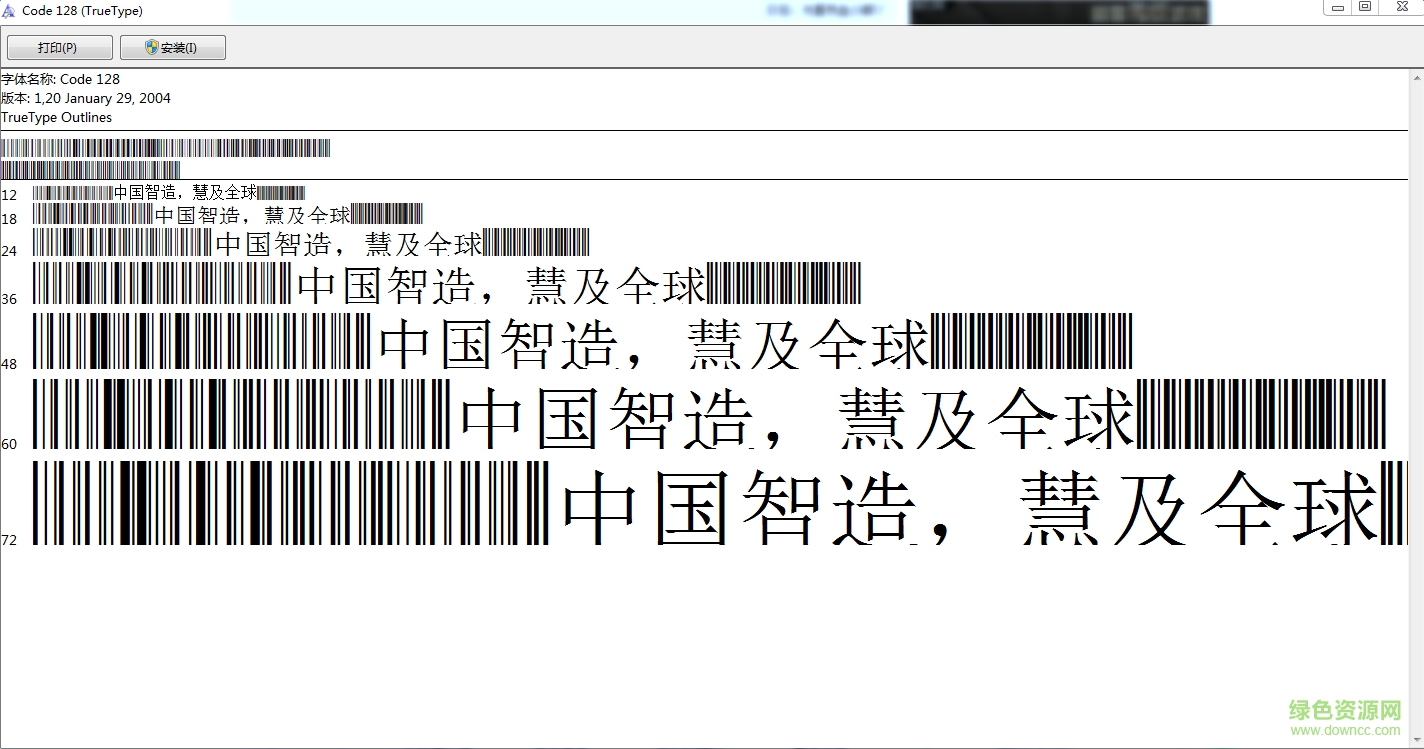
條形碼字體code128auto是一款應(yīng)用廣泛的條形碼字體,每個字母和數(shù)字都代表著不同的條碼,適用與物流控制系統(tǒng)、超市條碼印刷等各個方面,需要的朋友快來綠色資源網(wǎng)下載吧!
1.Code 128碼與Code 39碼有很多的相近性,都廣泛運(yùn)用在企業(yè)內(nèi)部管理、生產(chǎn)流程、物流控制系統(tǒng)方面。
2.不同的在于Code 128比Code 39能表現(xiàn)更多的字符,單位長度里的編碼密度更高。
3.當(dāng)單位長度里不能容下Code 39編碼或編碼字符超出了Code 39的限制時,就可選擇Code 128來編碼。
4.所以Code 128比Code 39更具靈活性。